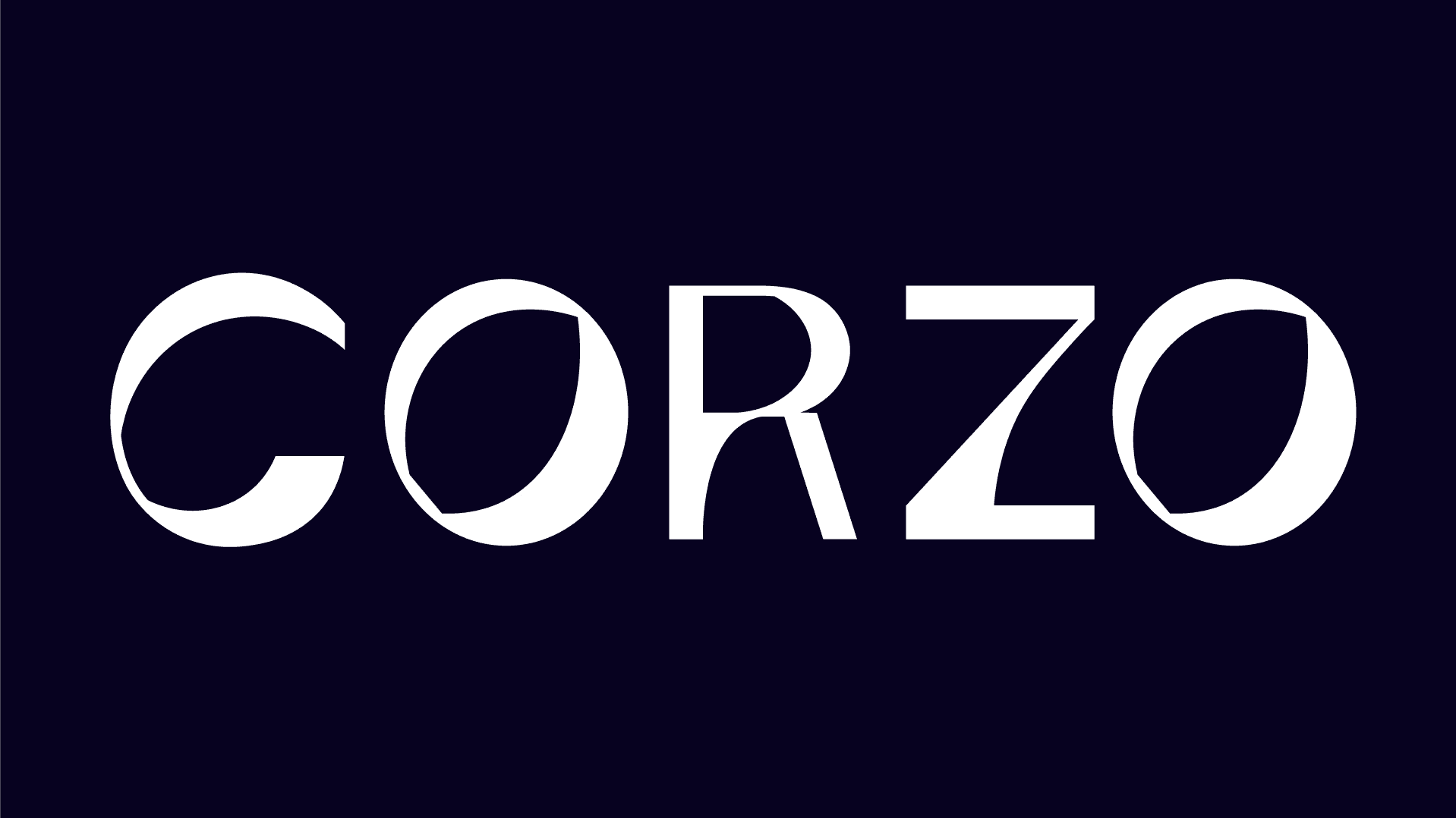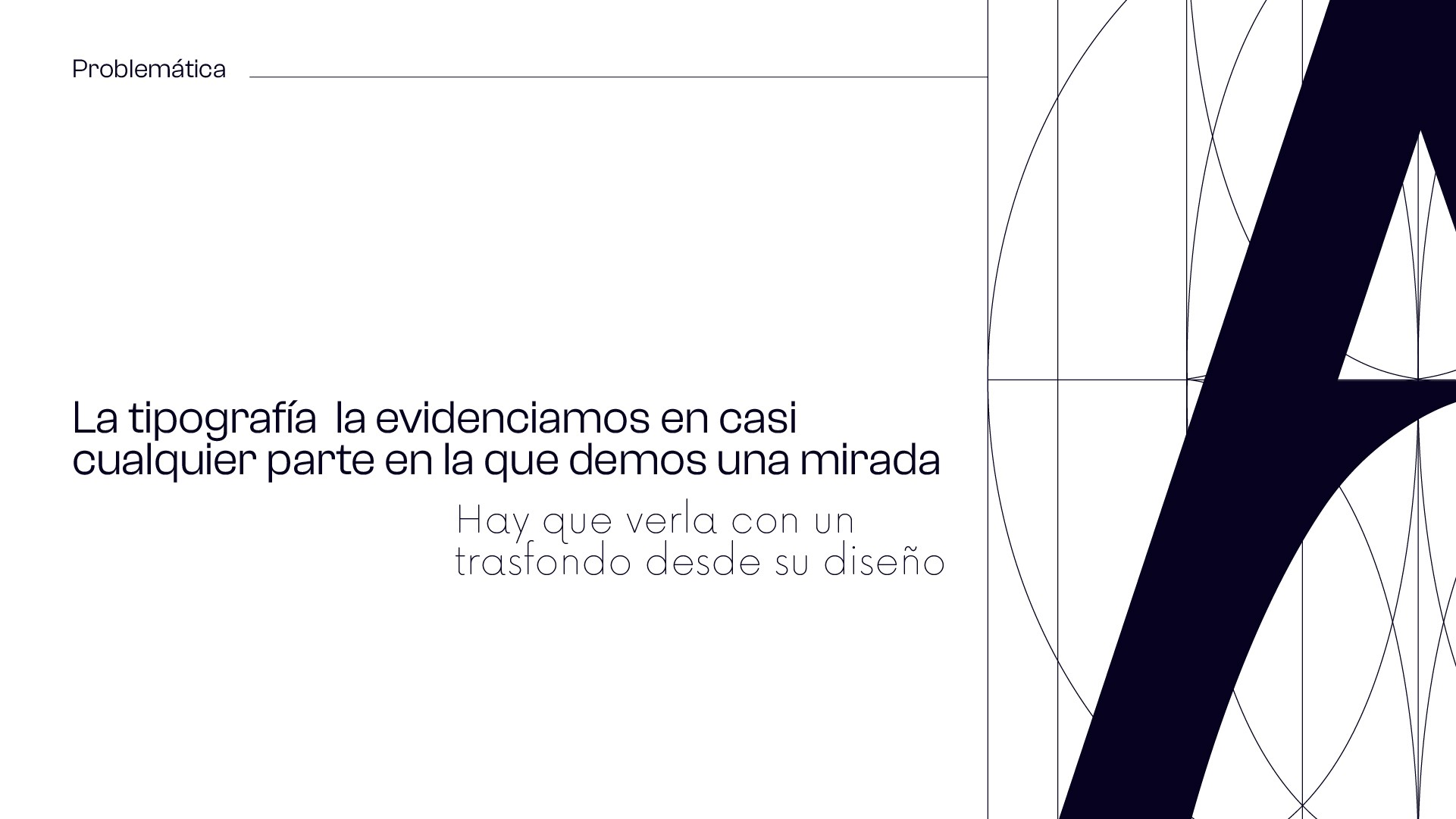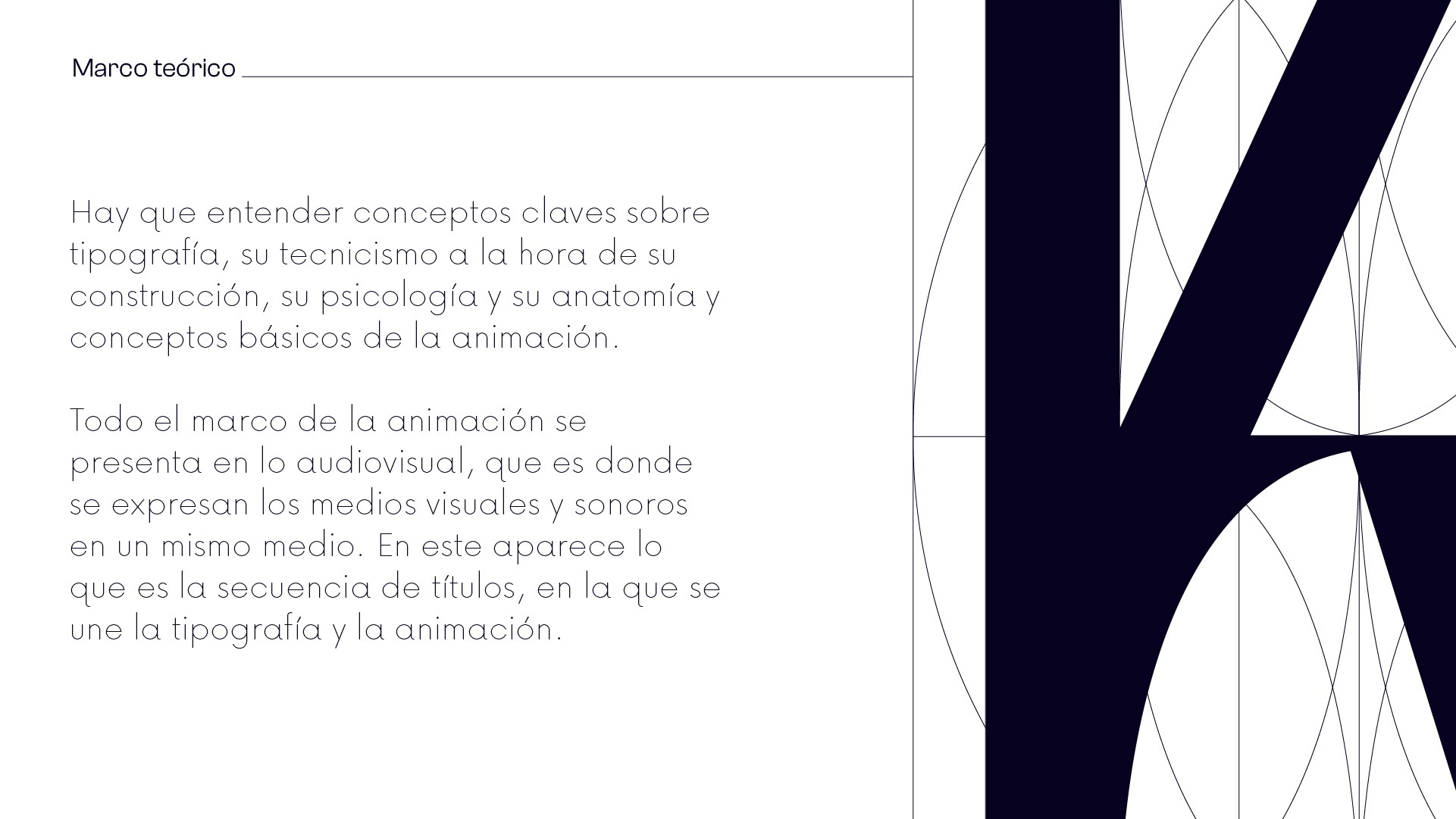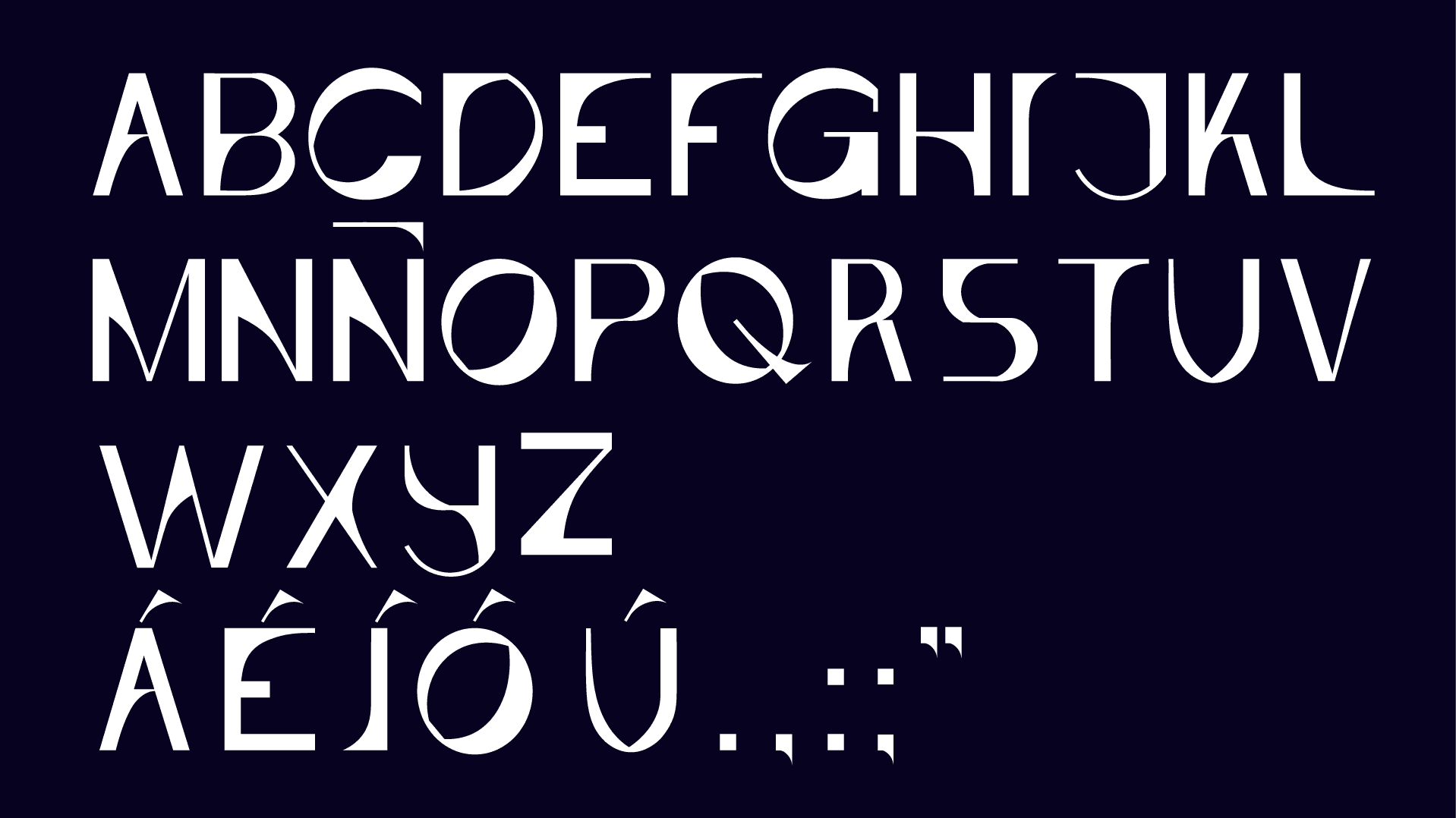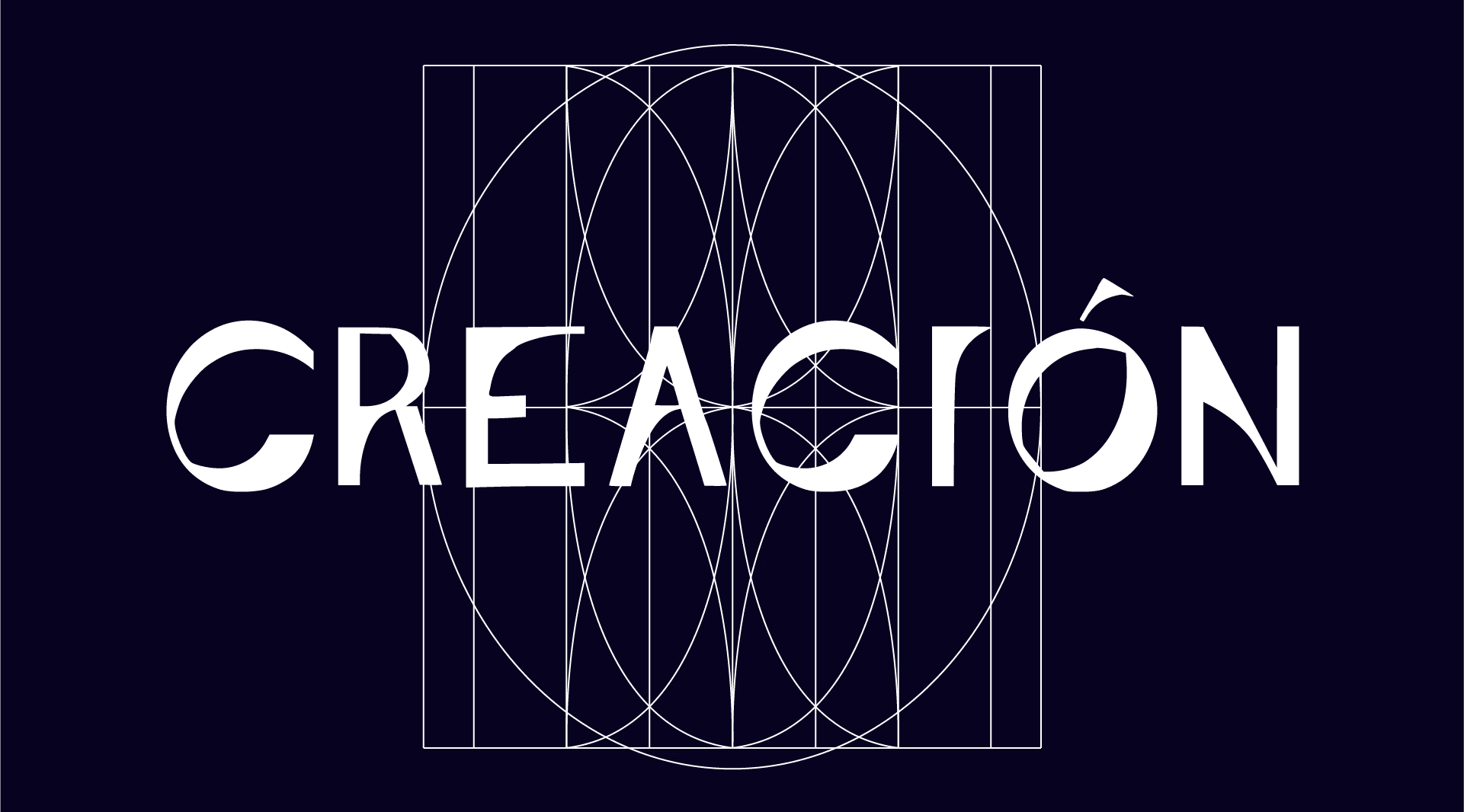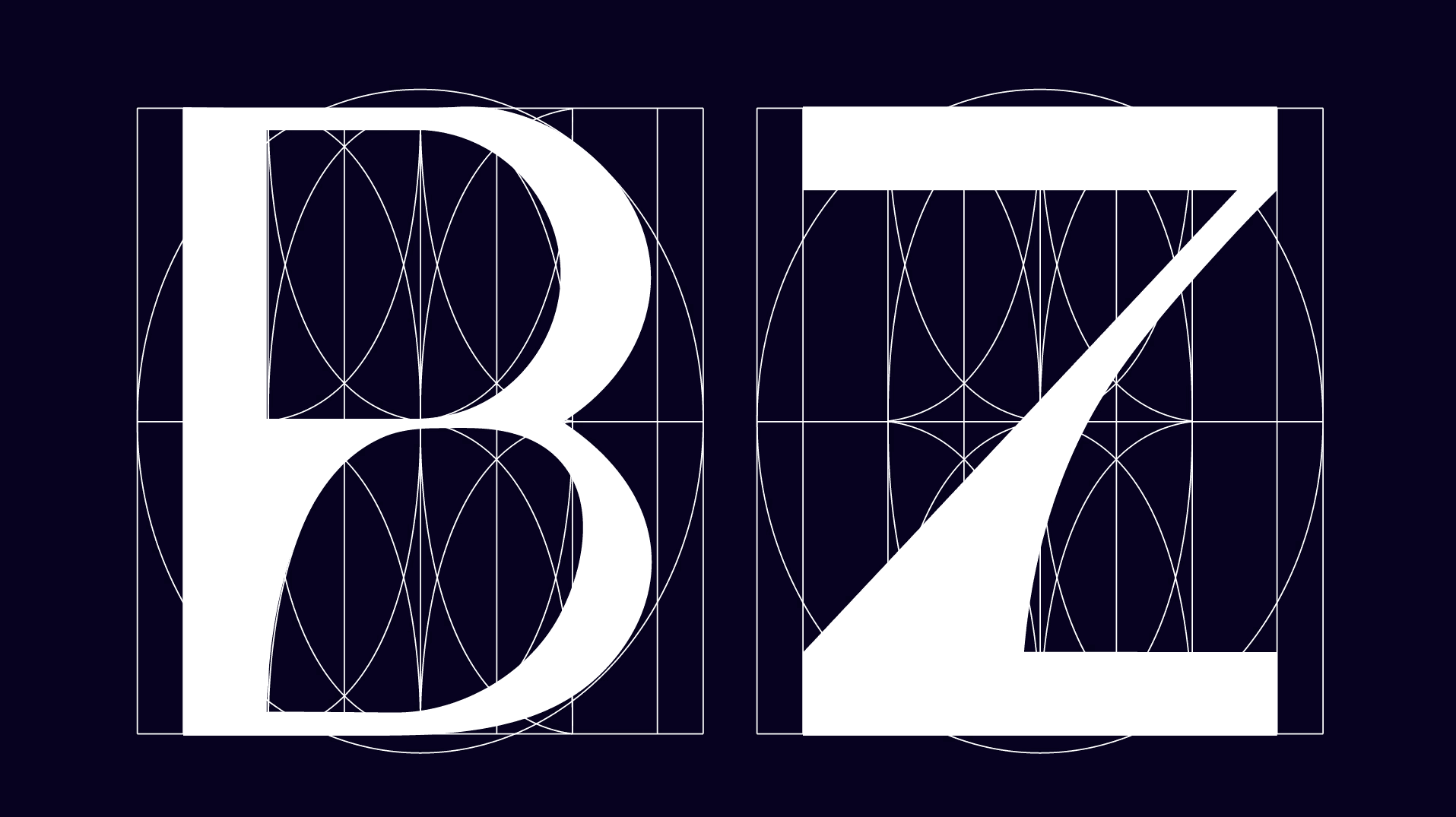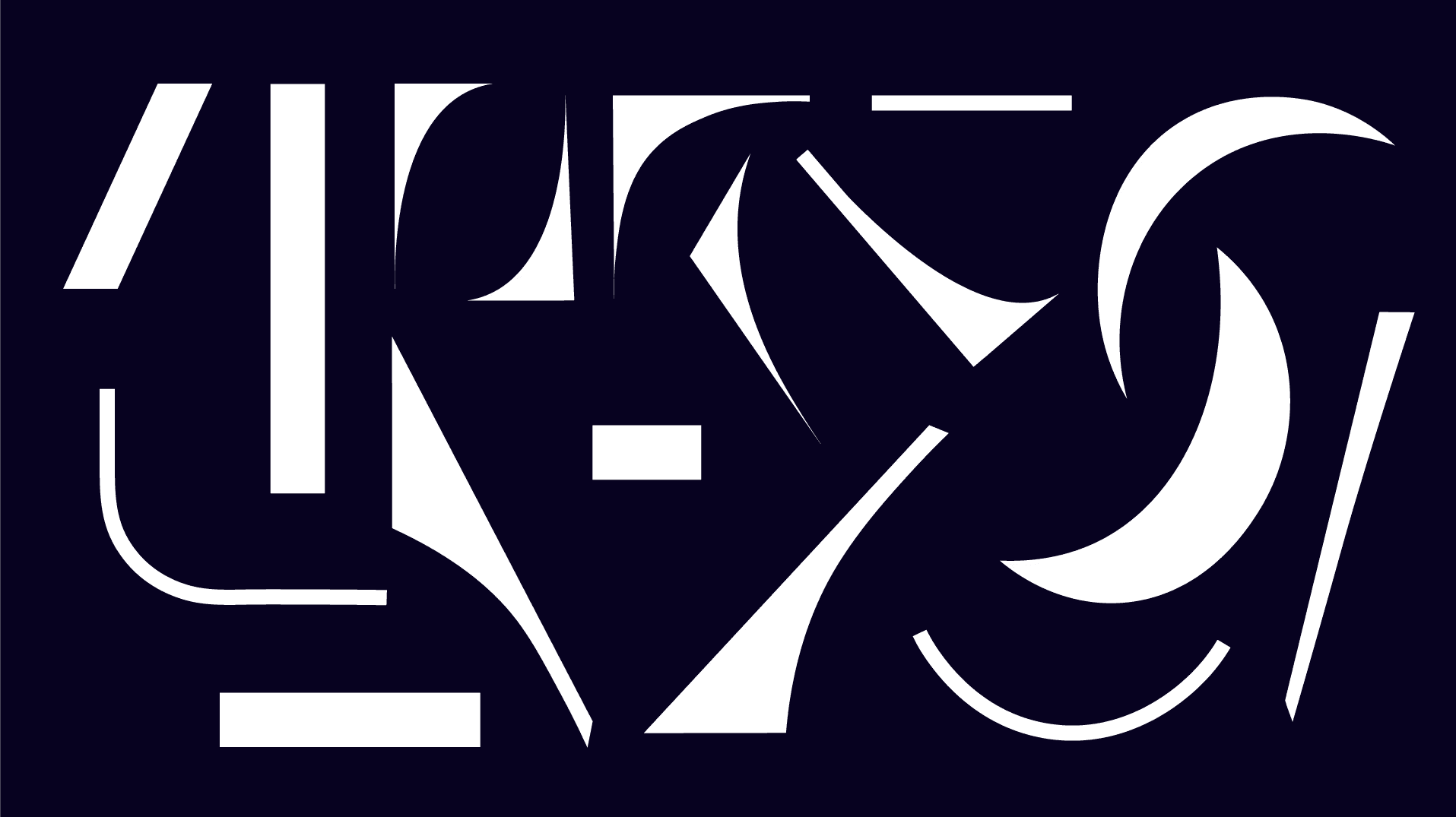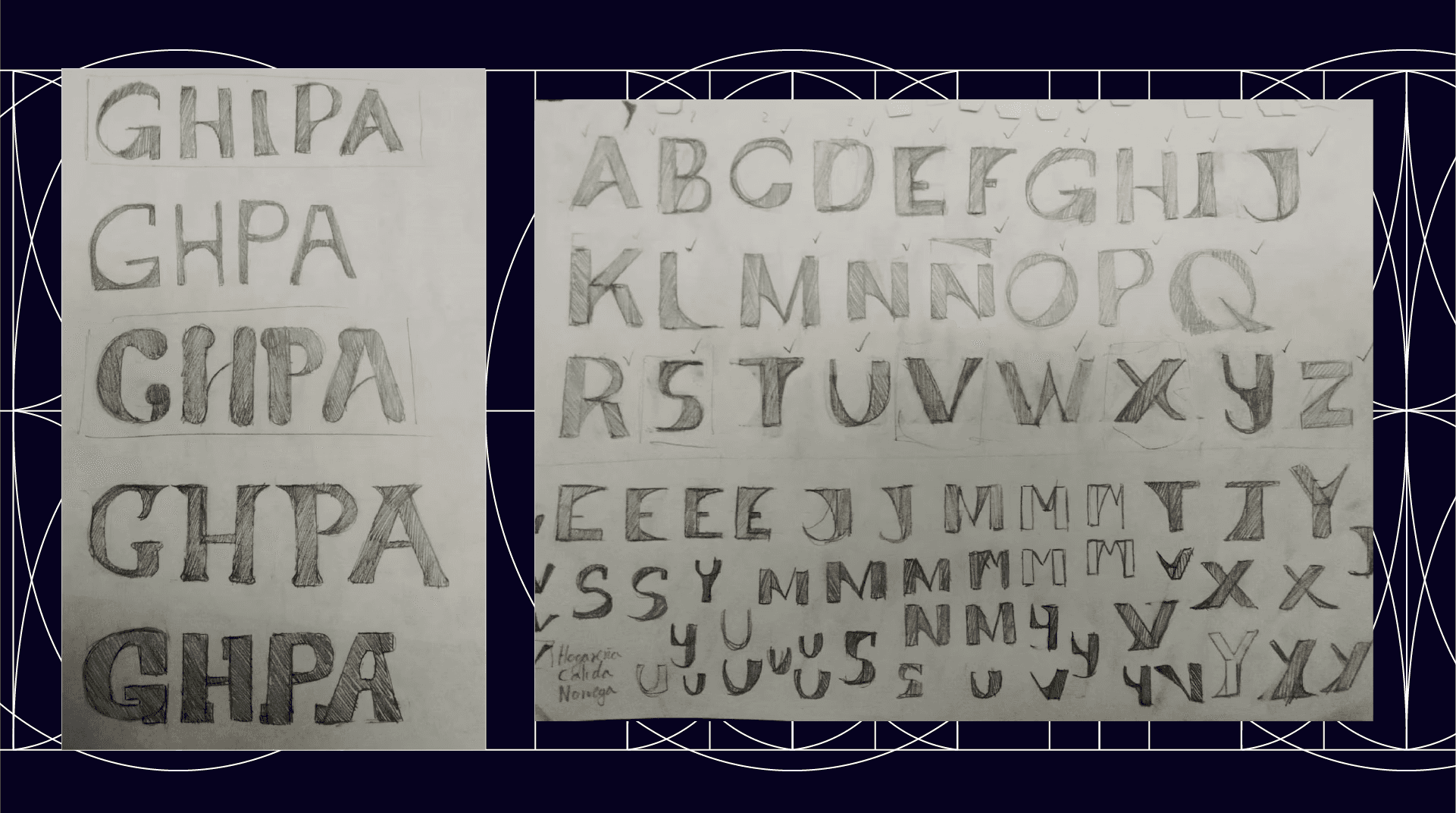
Proyecto de investigación y creación de un alfabeto completo tipográfico para el uso de la secuencia de título del semillero de investigación y creación: Ludomentis, de la Universidad Pontificia Bolivariana.